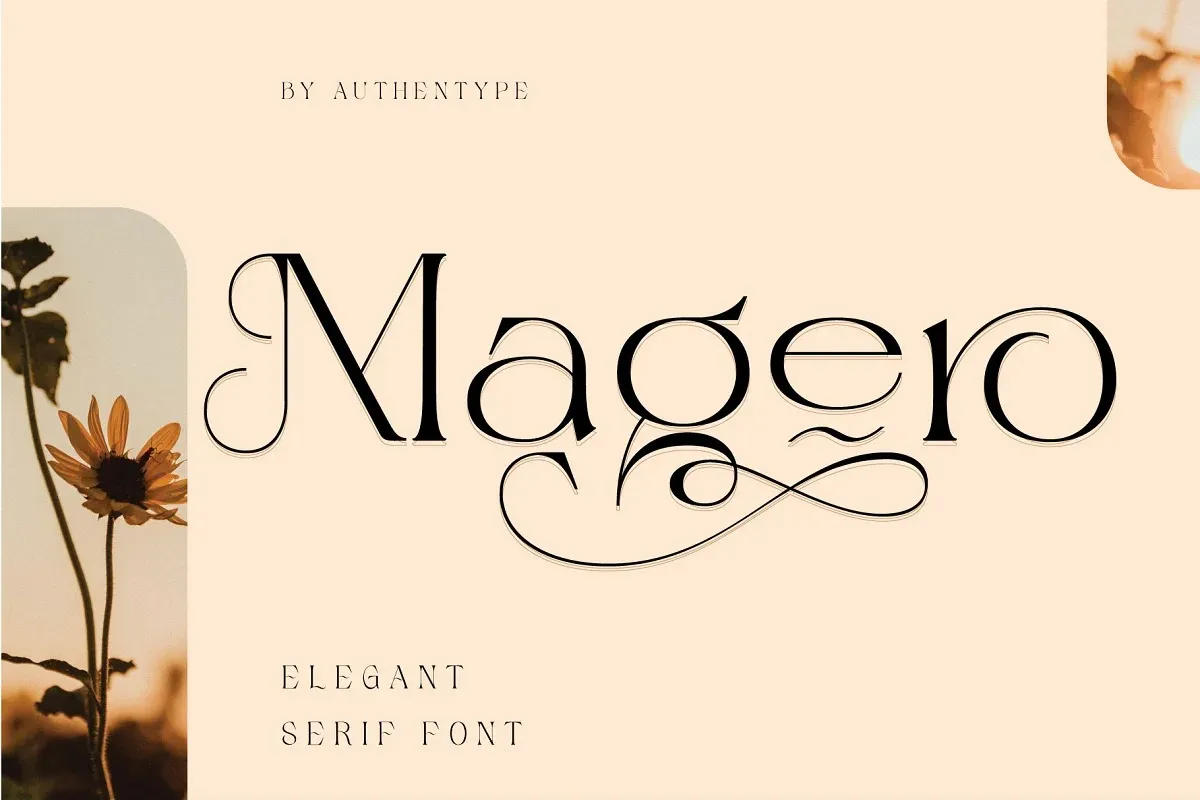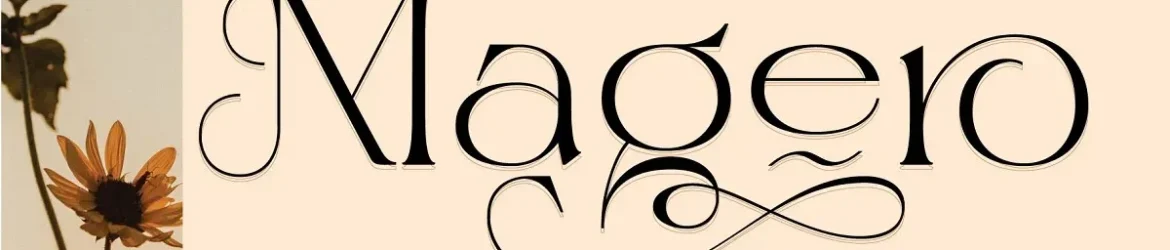
A fonte Magero Font é uma elegante tipografia serifada moderna desenvolvida pelo designer AuthenType. Seu uso multifuncional torna-a perfeita para diversas aplicações, incluindo desenhos de logomarca, posters e mídia promocional. Com seu traço estilizado, contrastante e limpo, a Magero Font é ideal para criar designs que chamem atenção e transmitam elegância. Este tipo de fonte, disponível desde o designer 99designs, oferece uma opção versátil para projetos de marketing e design gráfico.